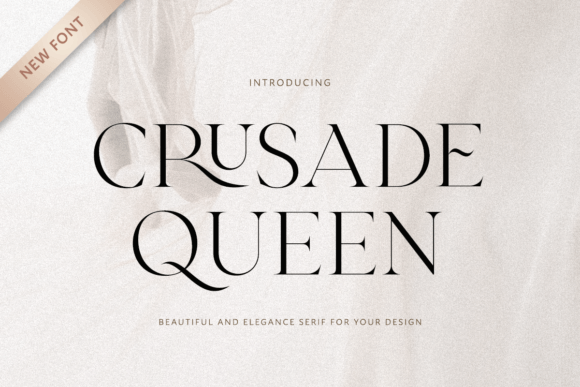
Crusade Queen
Jika anda sedang mencari aset berkualiti tinggi seperti Crusade Queen, pakej premium ini merupakan pilihan yang hebat untuk projek kreatif anda.
Sama ada anda mencipta produk POD (Print on Demand), jemputan perkahwinan atau grafik media sosial, Crusade Queen amat bersesuaian.